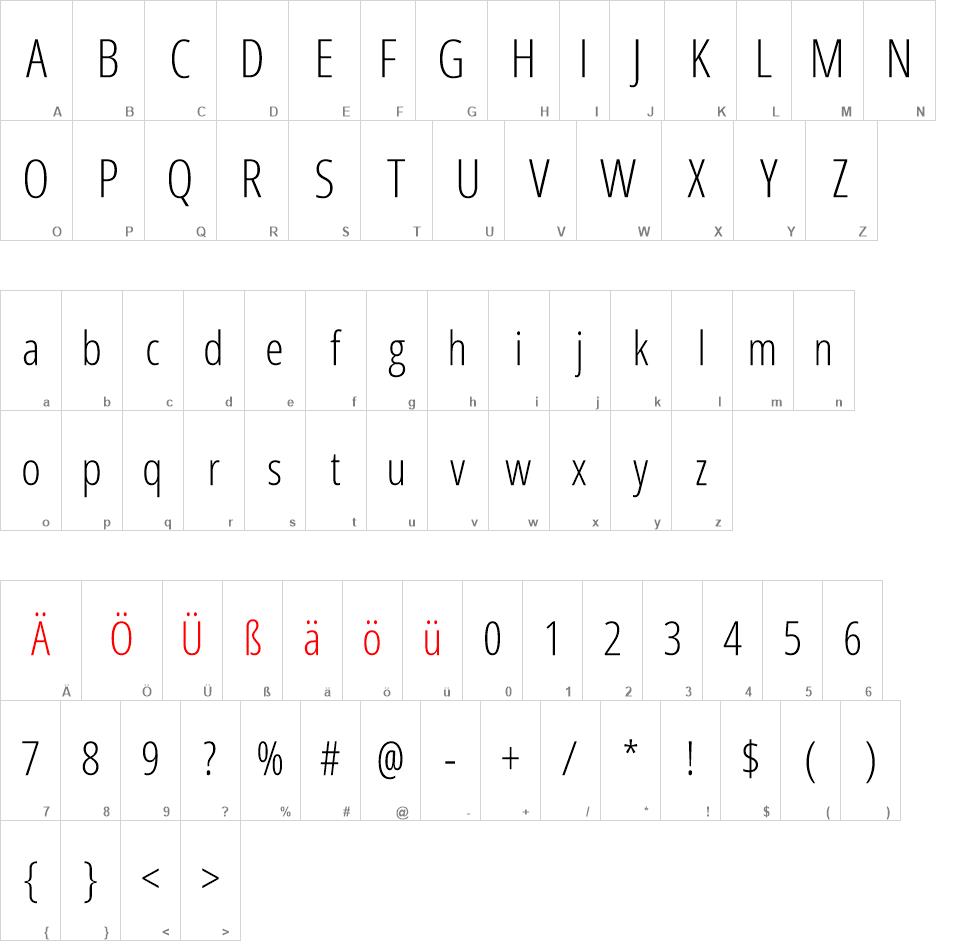
Open Sans Condensed
Open Sans Condensed font
Open Sans Condensed ist eine humanistische serifenlose Schrift, die von Ascender Corp Genre Director Steve Matteson entworfen wurde. Diese Version enthält den 897-Zeichensatz, der die Standard-ISO-Latin-1, lateinischen CE, griechischen und kyrillischen Zeichensätze enthält. Die Open Sans Condensed Schrift ist mit aufrechten Körperhaltungen, offenen Formen und einem neutralen, aber intimen Look gestaltet. Optimiert für Print-, Web- und Mobile-Interfaces. Hervorragende Lesbarkeit in Briefform.